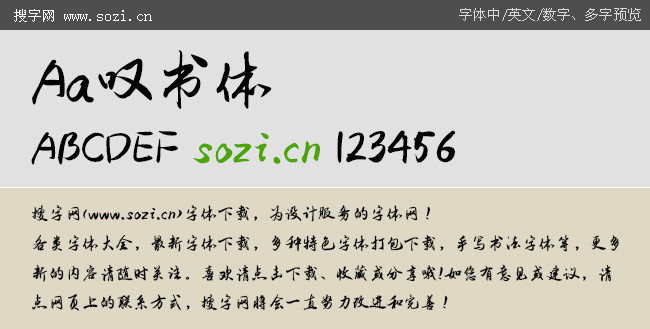
Aa嘆書體
搜字網(wǎng)給大家提供一款A(yù)a嘆書體中文字體下載,這是一款手寫風(fēng)格的書法字體,字體書寫自如,效果瀟灑大方,適合海報(bào)設(shè)計(jì)、包裝畫冊(cè)等宣傳廣告等應(yīng)用(此字體為個(gè)人非商用版,如需商用請(qǐng)聯(lián)系作者購(gòu)買版權(quán))。